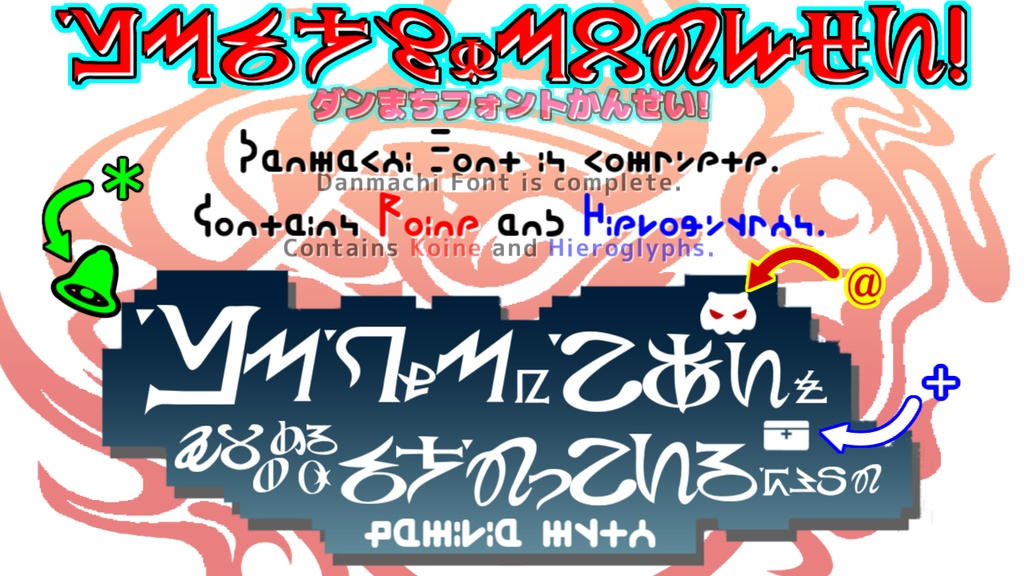
ダンまちフォント
このフォントは『ダンジョンに出会いを求めるのは間違っているだろうか』の作品内で登場する 『共通語(コイネー)』、『神聖文字(ヒエログリフ)』をモチーフとして作成しています。 ●対応文字リスト(全角・半角同一) ひらがな・カタカナ(神聖文字に対応) 大小アルファベット(共通語に対応) 以下の記号↓ ( ) , . / ! ? " ' - _ ・ : ; ` = | \(バックスラッシュ) ※特殊仕様・・・・・・以下の文字は特殊な記号に置き換えています。 ¥$ → ヴァリス記号 @ → ダンまちロゴ内のモンスター型アイコン + → ダンまちロゴ内の手紙型アイコン * → ダンまちIIIロゴ内のベル型アイコン その他文字・記号は対応していません。 追記: 一部文字を追加 ヷヺ ひらがな・カタカナの区別化(アニメ準拠:かな→正位置 / カナ→逆位置) ●クレジット ~参考にした投稿~ ○共通語 ・ぱんかれ 様のX(旧Twitter)での投稿 https://x.com/pcb/status/616085186183168001 ・アニメ内映像 ○神聖文字 ・Nekomancer 様のPixiv内での投稿 https://www.pixiv.net/artworks/50216256 ・アニメ内映像 ○特殊記号 ・ぱんかれ 様の上記投稿(ヴァリス記号) ・ダンまち作品のロゴ ~使用ソフト~ ・gimp 2.10 ・fontforge 制作: Hydrogen ※このフォントの商用利用は問題ありませんが、「ダンまち公式」の規約に基づき活動を行ってください。 ※このフォントでの創作を行った際、YouTube等の媒体で使用した際は概要欄等にクレジットの記載をお願いしています。